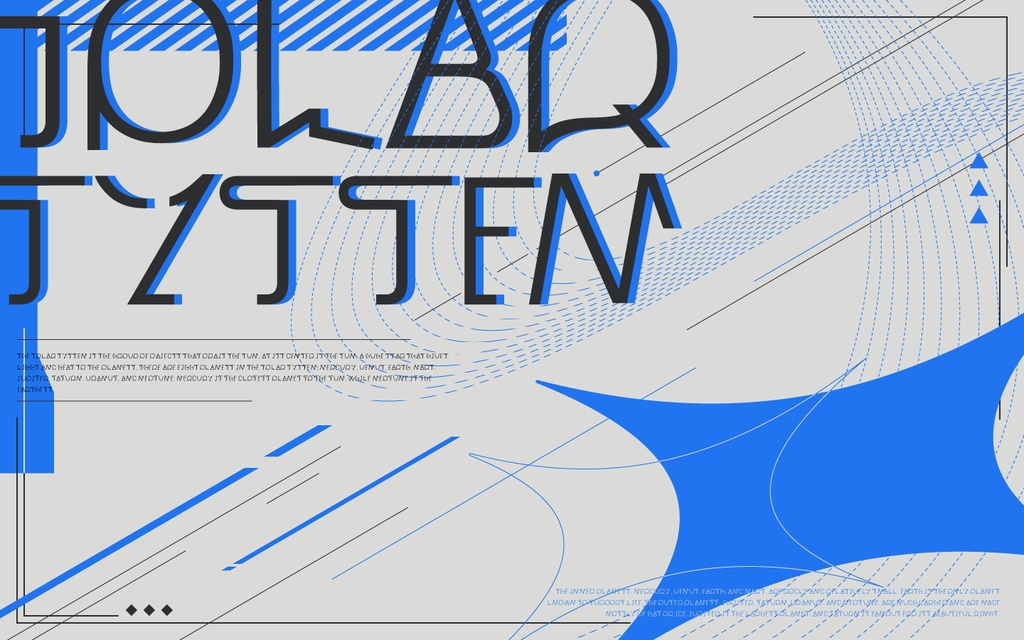
DUALPHA/アルファベットフォント
16種類の形しかないのに、31種類の文字・記号が入力できるという不思議なフォントです。アルファベットの大文字全26字と「,」「.」「'」「?」「!」が収録されています。 -利用について 商用利用 → OK 再配布 → NG AI学習 → NG 使用時の連絡 → 不要(もし使ってくれたら、@tochi2718をつけてツイートしてもらえると非常に嬉しいです! 僕が飛んでいきます) -収録文字一覧 ABCDEFGHIJKLMNOPQRSTUVWXYZ ,.'?! 追記 2026/02/27 QuizKnockさんの記事にて、こちらのフォントが取り上げられました! DUALPHA含む、不思議な形をした様々なフォントで問題文が書かれています。ぜひ読んでみてください! https://web.quizknock.com/font_quiz